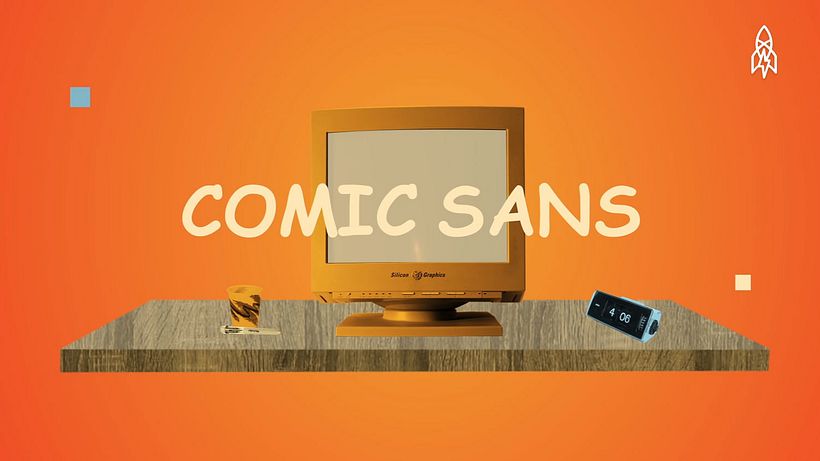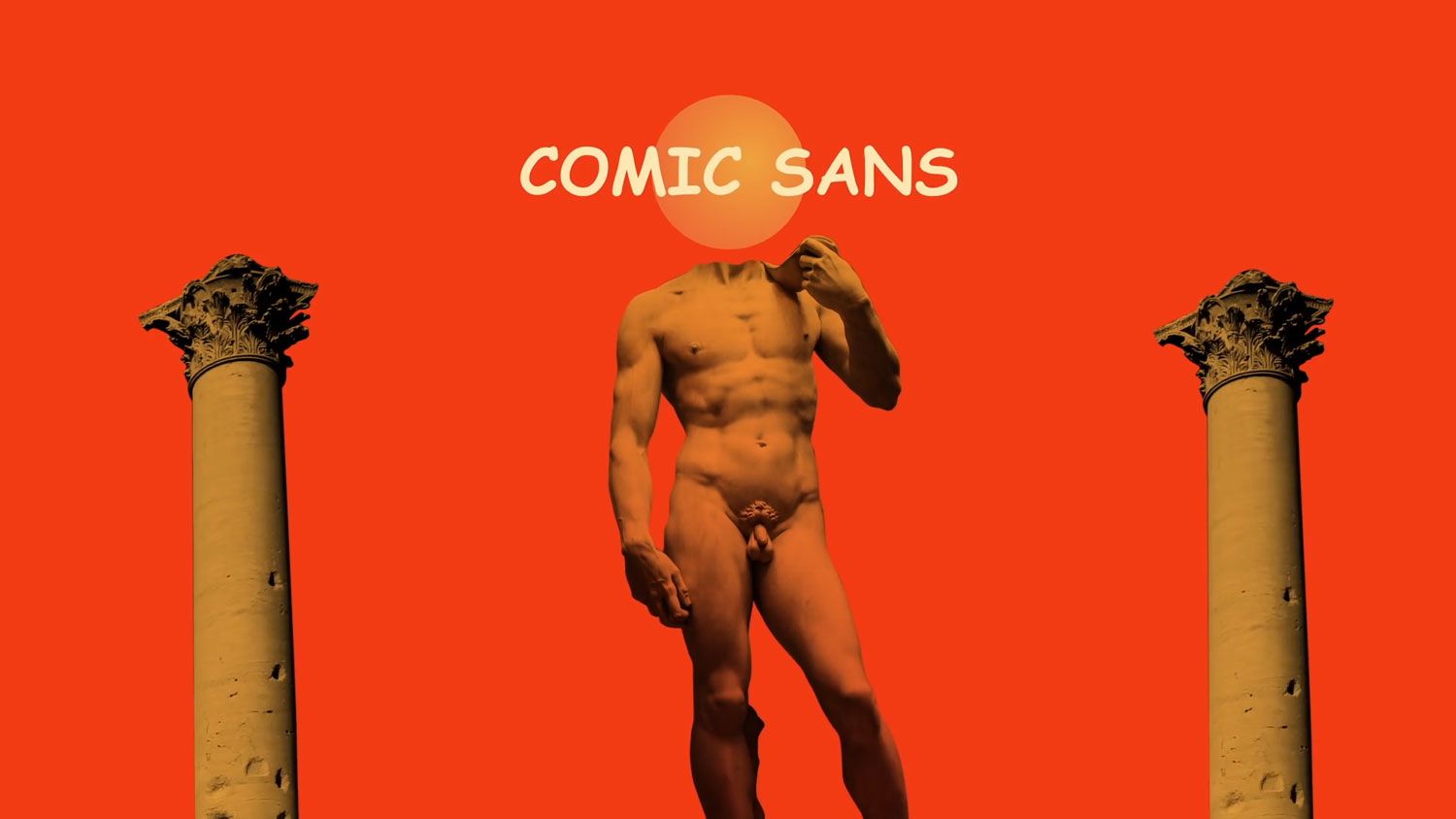
¿Quién y por qué diseñó la tipografía Comic Sans?
La has visto miles de veces. En la calle, en internet, incluso en tu casa... esta tipografía está en todas partes.
Independientemente de tu edad y de cuántos años lleves enganchado al mundo del diseño, nos atrevemos a asegurar que conoces la tipografía Comic Sans y que, con toda probabilidad, tengas una opinión formada sobre ella. Fue creada en 1994 por Vincent Connare, que por aquel entonces trabajaba como ingeniero tipográfico para Micorsoft y es, casi con seguridad, una de las fuentes tipográficas más famosas de todos los tiempos. El minidocumental 'Comic Sans: The Man Behind the World’s Most Contentious Font' habla de quién, cómo y por qué diseñó el tipo de letra más odiada por diseñadores de todo el mundo.
Resulta sencillo adivinar que Vincent Connare se inspiró en los comics de la época para diseñar la tipografía Comic Sans, concretamente en los de Batman y Watchmen; y lo hizo movido por el deseo de crear un tipo de letra diferente, que no dejase indiferente a nadie. ¡Y vaya si lo consiguió!
Él mismo confiesa que se sorprendió al empezar a ver su tipografía en todo tipo de soportes. Recuerda que su primera aparición fue en un cartel de neon que vendía sellos de caucho divertidos, más tarde Comic Sans terminaría convirtiéndose en la tipografía elegida para ilustrar toallas de playa, monumentos conmemorativos, letreros institucionales, logotipos... de todo el mundo. El propio Vincent Connare confiesa que no es su mejor diseño pero, si atendemos a su repercusión sí es una obra de arte.